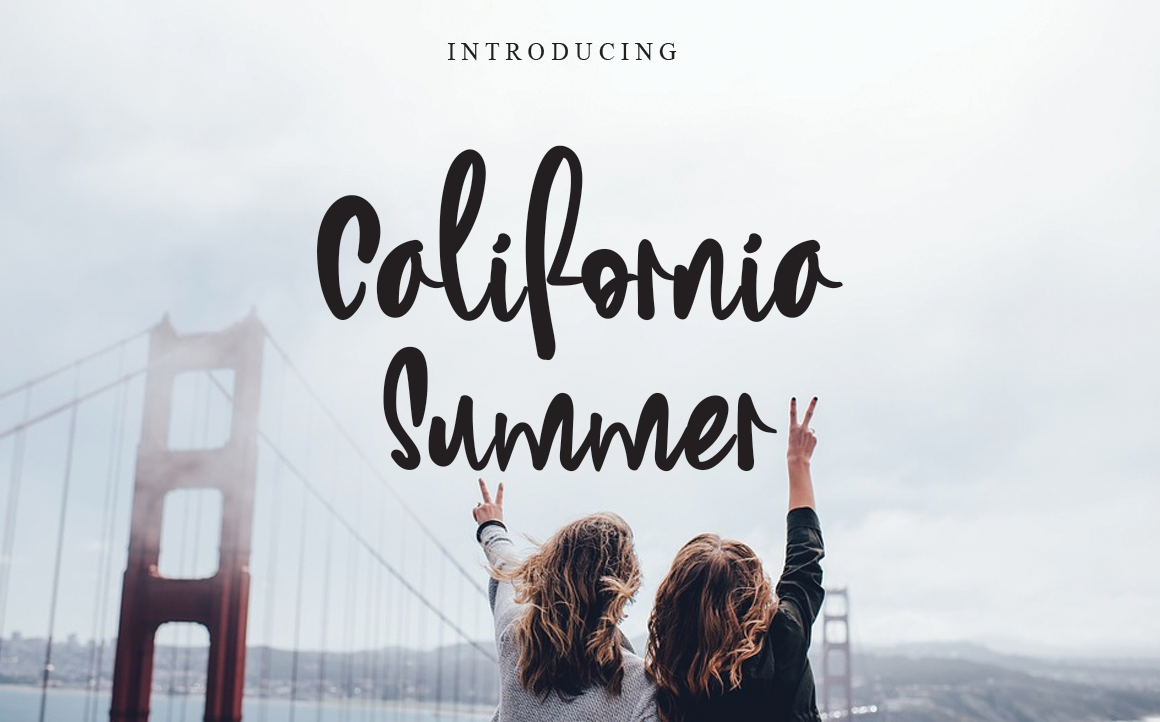
California Summer Font – Download Grátis
Esta é uma fonte escrita à mão única, divertida e agradável. Seja para criar conteúdo nas redes sociais, especialmente no Instagram, ou para adicionar detalhes artesanais a projetos DIY, esta fonte irá transformar qualquer ideia criativa em arte genuína! Para quem está procurando uma fonte atraente e versátil que pode ser usada tanto nas redes sociais quanto em trabalhos manuais, a California Summer Font é o seu parceiro perfeito. Suavemente elegante e cheia de personalidade, ela enriquece qualquer texto com um toque único. Seja para adicionar uma pitada de originalidade ao seu post no Instagram ou para tornar um projeto DIY ainda mais especial, esta fonte escrita à mão é a escolha certa.